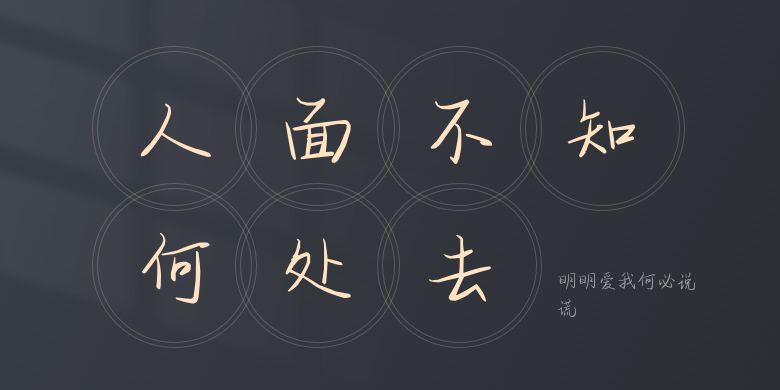
明明爱我何必说谎
明明爱我何必说谎,这款字体结构工整、笔画清晰,兼顾美观与易读性,适用于标题、正文、海报、包装、LOGO 等多种场景。字形优雅稳定,风格百搭耐看,适配日常排版与创意设计,让文字呈现更舒适、更具质感。明明爱我何必说谎一笔一画,皆是细节,以均衡的比例、流畅的线条打造舒适视觉体验,字形端正大气,风格简约现代。无论是商业设计、品牌宣传还是日常排版,都能轻松驾驭,让文字更有格调与力量。明明爱我何必说谎字体下载。